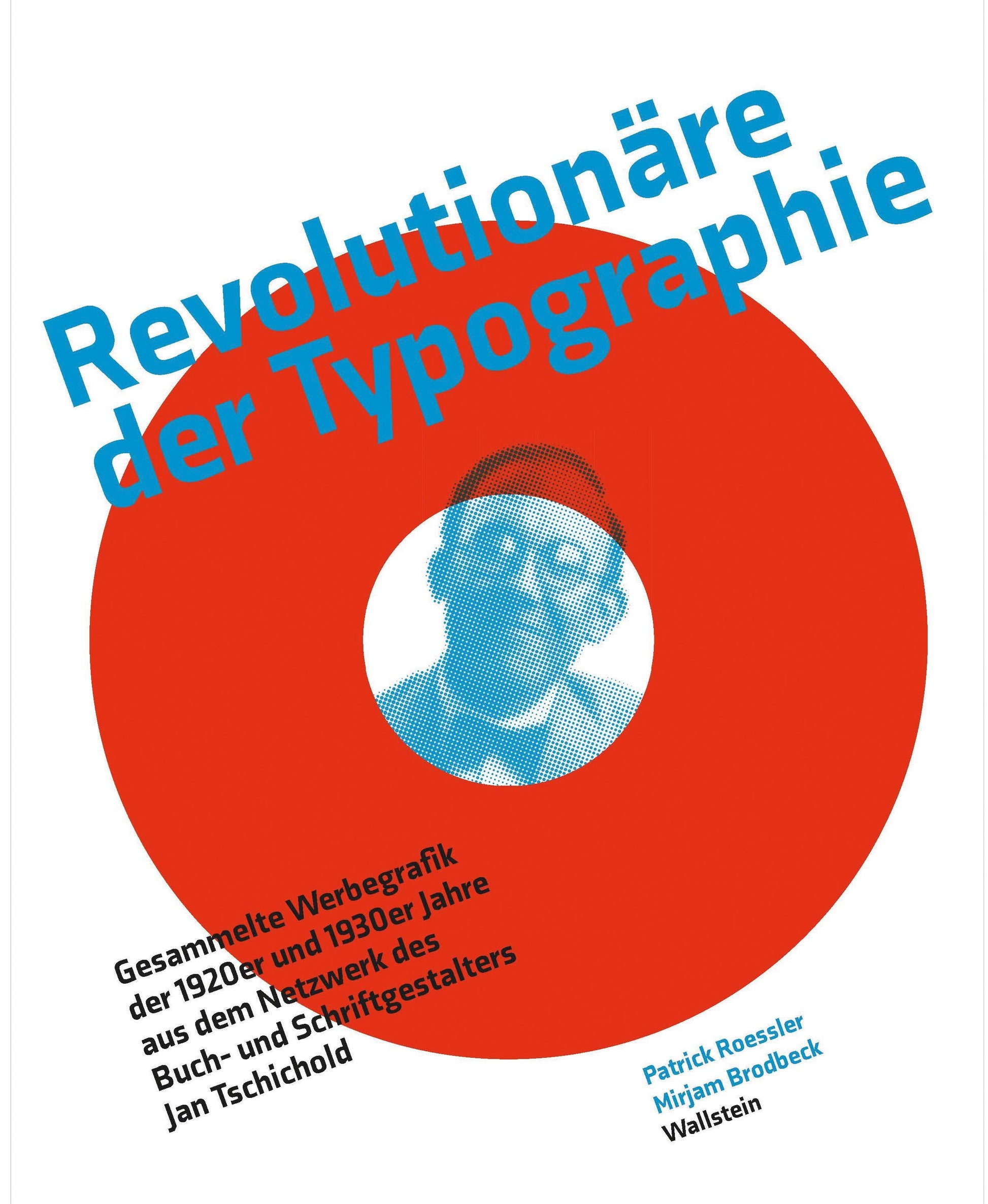
Weltklasse-Grafikdesign aus den bis heute stilprägenden 1920er und 1930er Jahren: die Sammlung Jan Tschichold der Schule für Gestaltung Basel.Innerhalb eines europäischen Netzwerks der Avantgarde zusammengetragen, enthält die »Vorbilder-Sammlung« des deutsch-schweizerischen Typografen Jan Tschichold rund 1.500 kleinformatige Drucksachen. Vertreten sind berühmte Gestalter aus dem Bauhaus-Umfeld wie László Moholy-Nagy und Herbert Bayer, ebenso Künstler wie Kurt Schwitters und El Lissitzky - allesamt Pioniere des modernen Grafikdesigns. Patrick Rössler und Mirjam Brodbeck zeigen erstmals den kompletten Bestand und präsentieren über 300 wichtige Arbeiten in großformatigen Abbildungen und zusätzlichen Erläuterungen. Sie ermöglichen das Studium der Originale, die die Aufbruchsstimmung jener Epoche greifbar machen und die in Tschicholds Büchern meist nur in schwarz-weiß oder in stark veränderter Farbgebung abgebildet sind. So weitet sich der Blick auf ein Netzwerk von 45 Gestaltern und auf ein Kapitel der europäischen Avantgarde, das den »Swiss Style« der Nachkriegszeit unmittelbar beeinflusste.